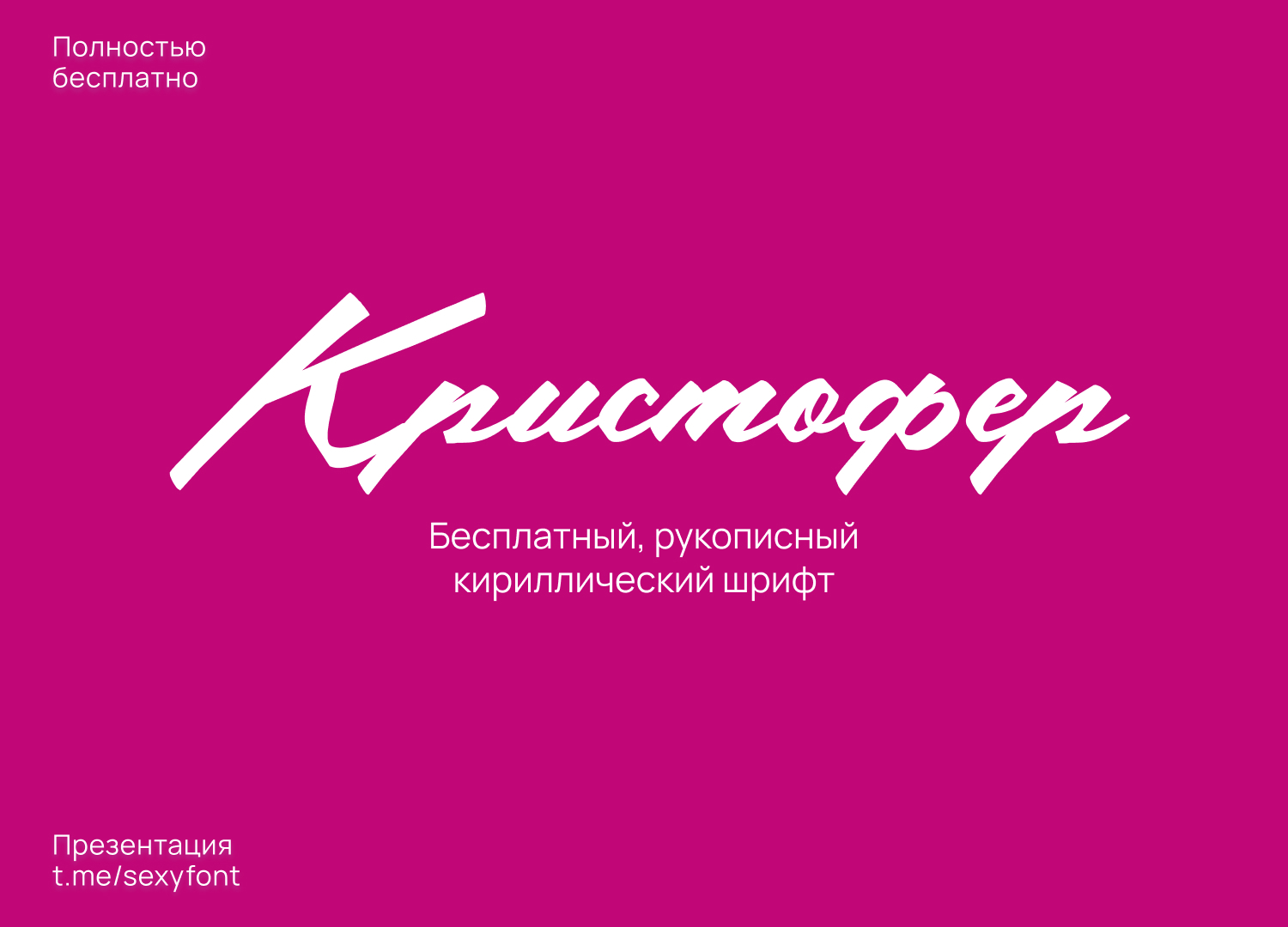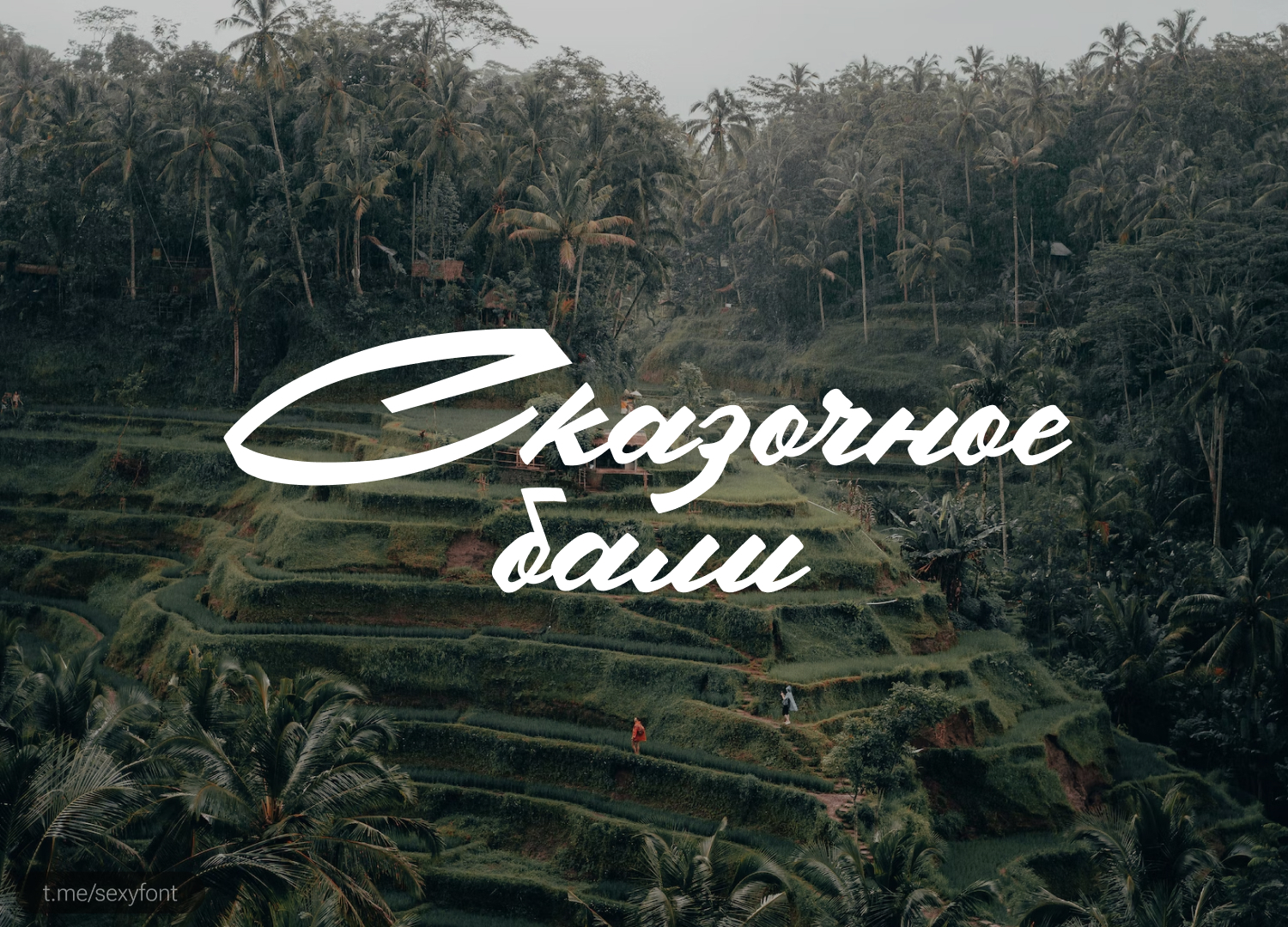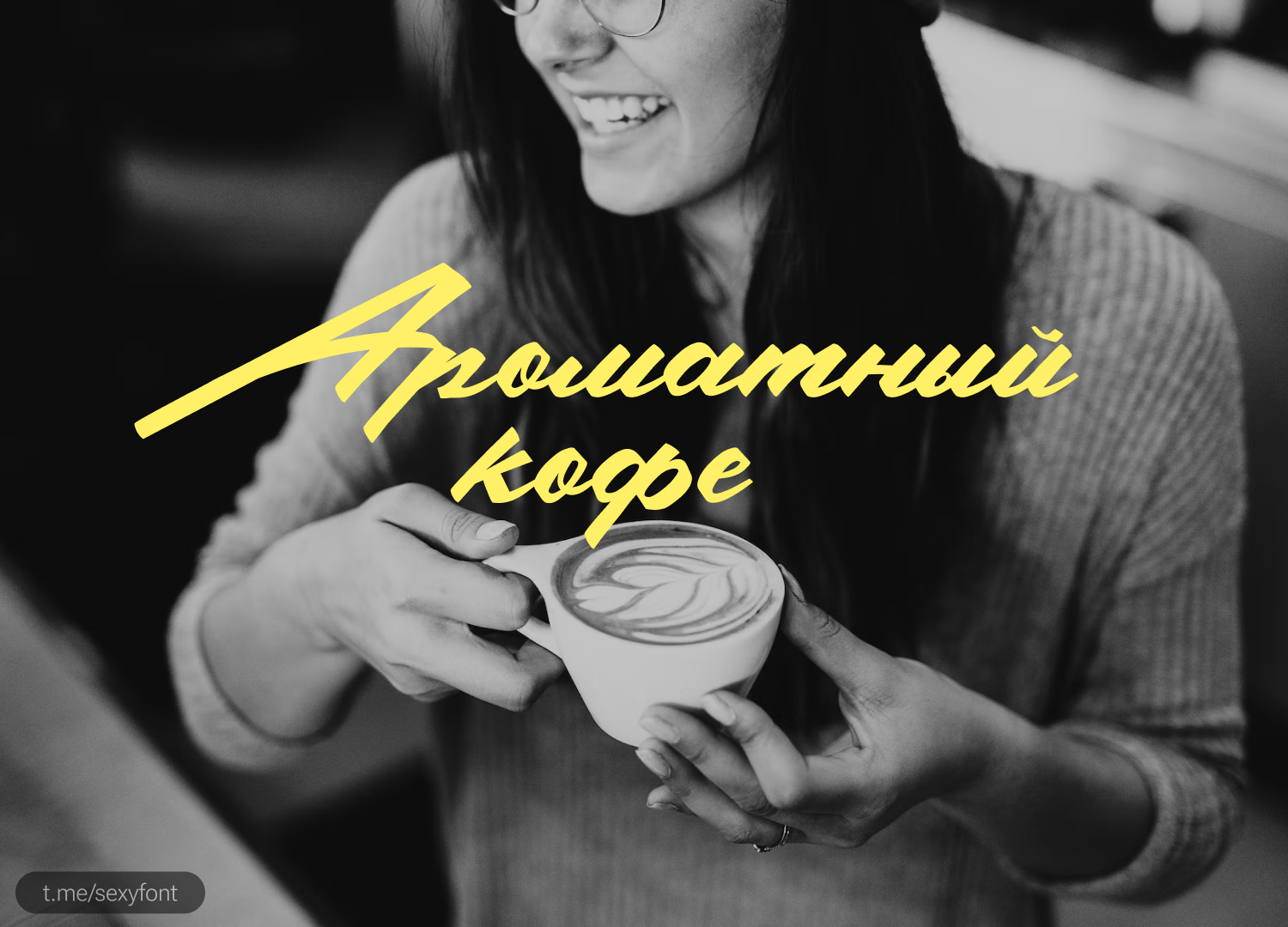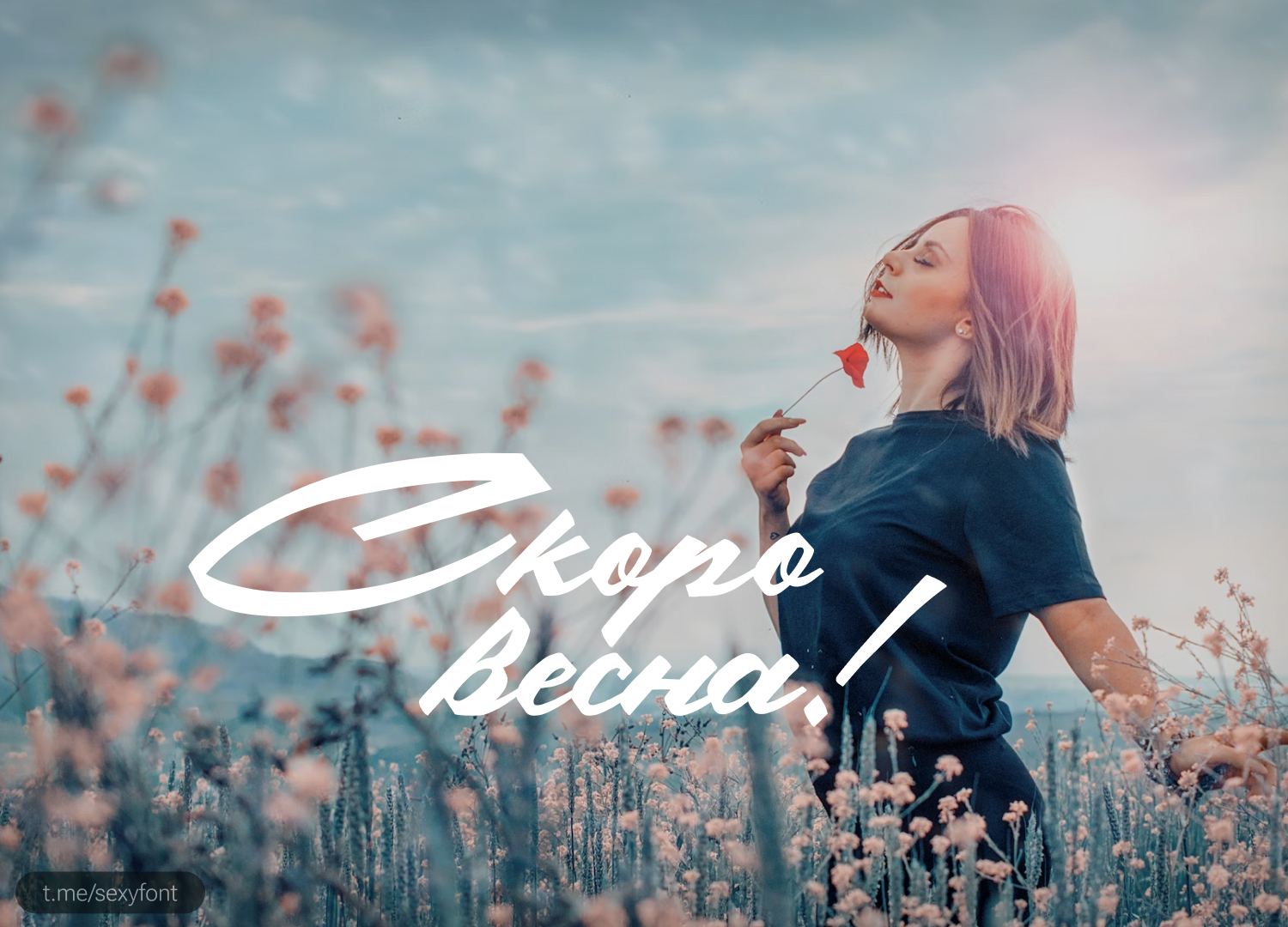
Шрифт Кристофер
Давно у нас не было рукописных шрифтов) Держите. Красивая кириллизация шрифта Кристофер. Отлично подойдет под открытки, приглашения, и короткие фразы. Читаемость конечно далеко не самая идеальная, но на то и рукописный)